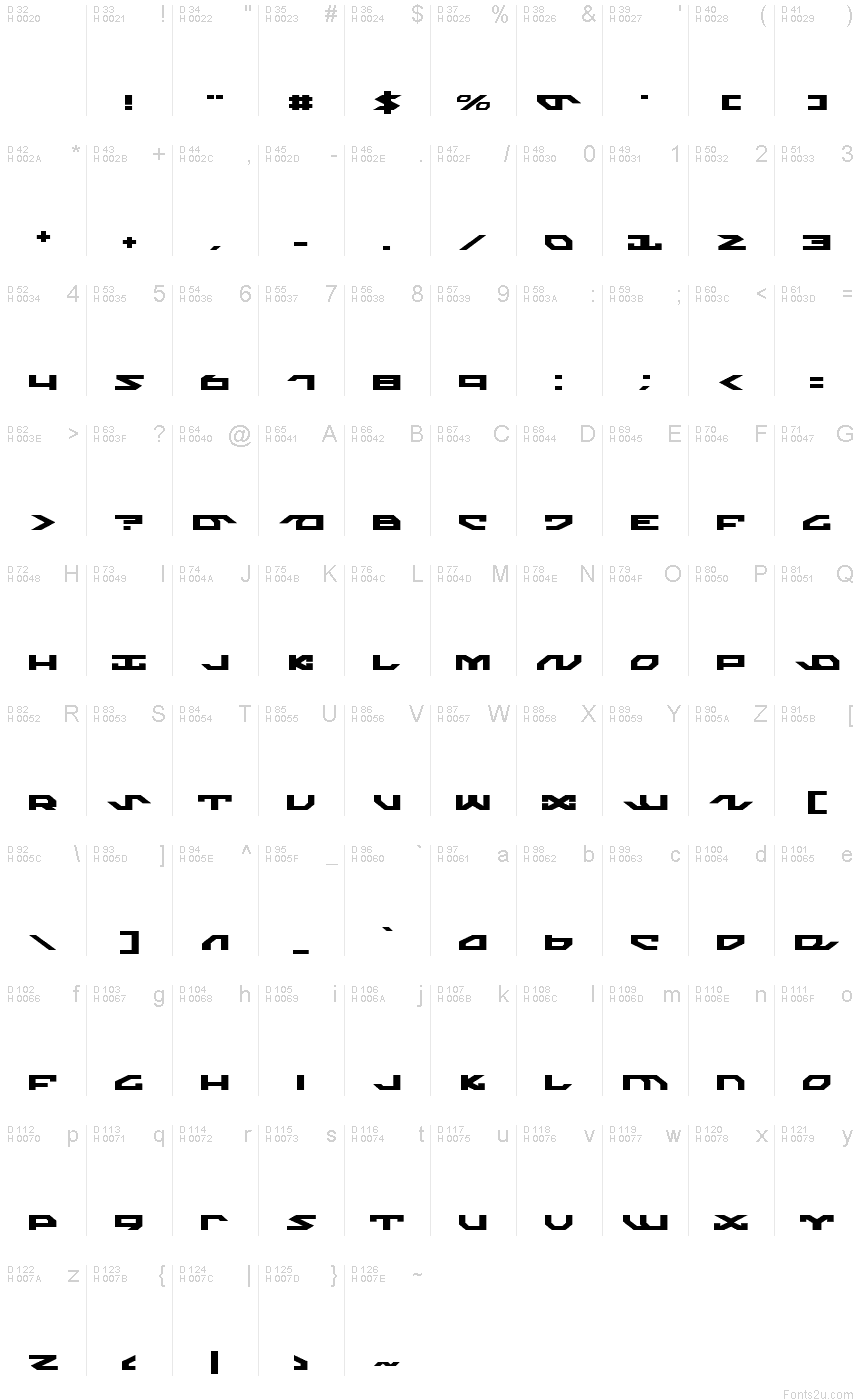
Nightrunner Expanded od Iconian Fonts to darmowy, futurystyczny font typu display o surowym, arcade’owym charakterze. Litery zbudowane są z szerokich, kwadratowych bloków i ostrych, diagonalnych cięć, co nadaje krojowi szybki, techniczny rytm, bardziej przypominający grafikę z paneli sterowania czy stare filmy science-fiction niż zwykłe napisy dekoracyjne.
Ten darmowy font najlepiej sprawdza się tam, gdzie nagłówek ma pełnić rolę graficznego obiektu: logotypy gier, tytuły filmów, plakaty technologiczne, okładki albumów czy branding dla streamerów idealnie pasują do jego kompaktowego, mechanicznego stylu. Używaj go w krótkich słowach, nagłówkach lub monogramach, jeśli chcesz, aby kanciaste kształty wykonały całą robotę i nadały projektowi dynamicznego charakteru.
Nightrunner Expanded